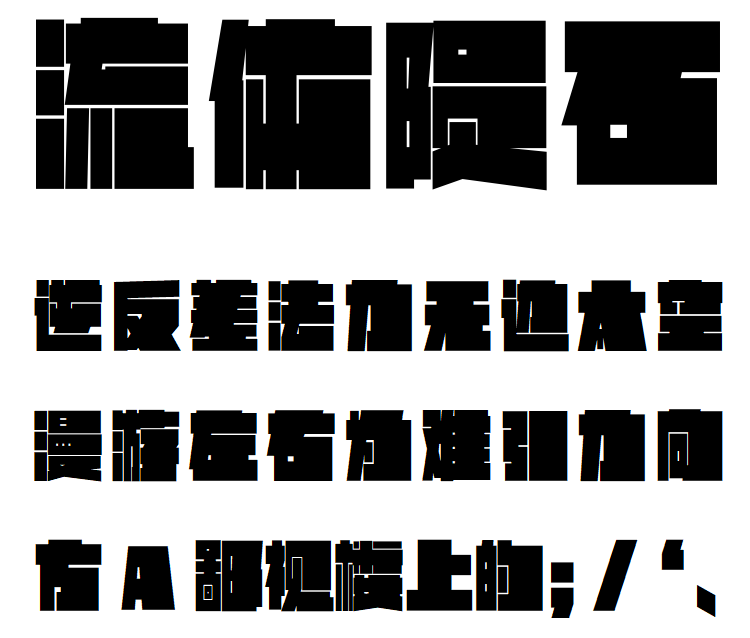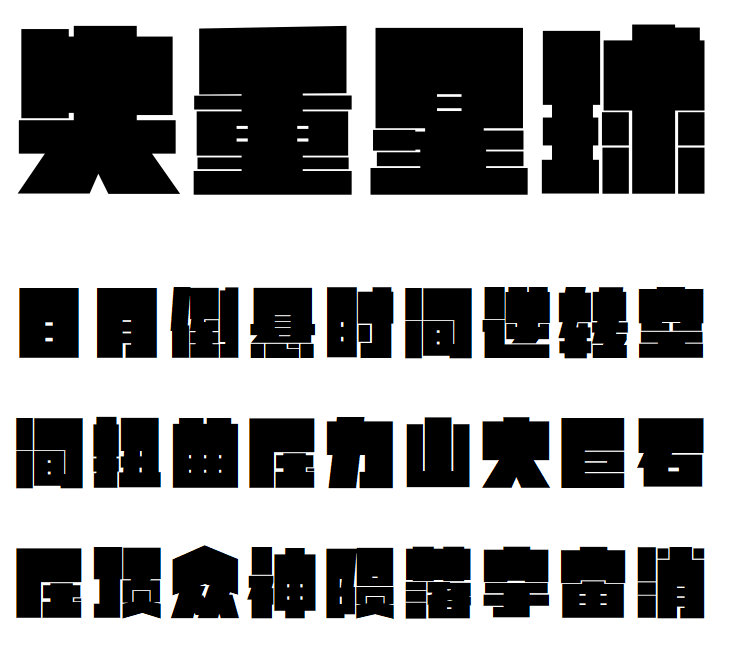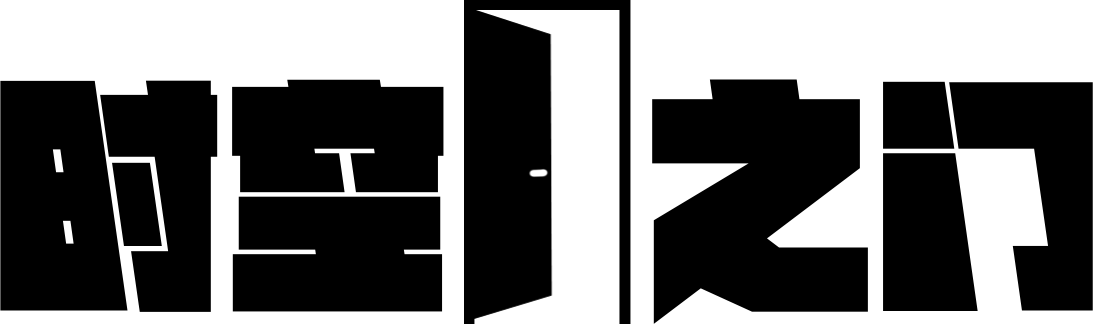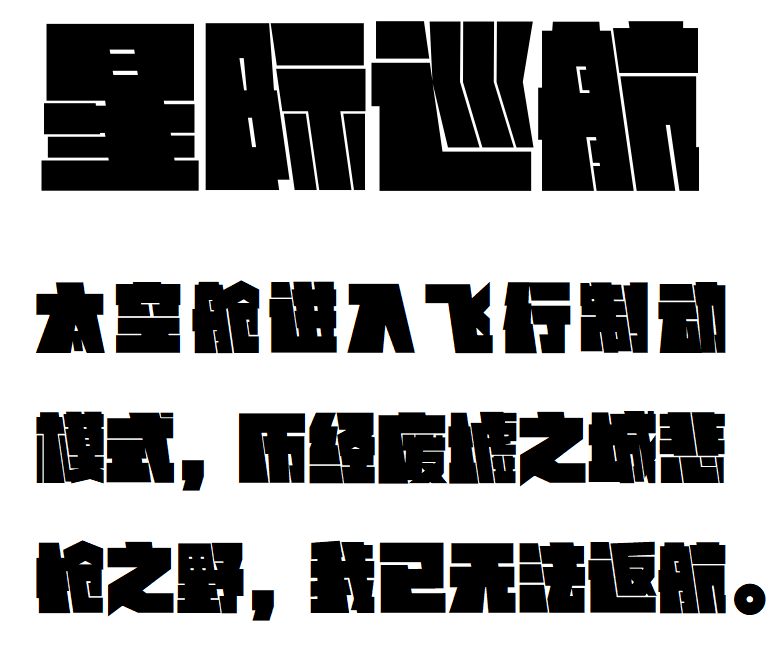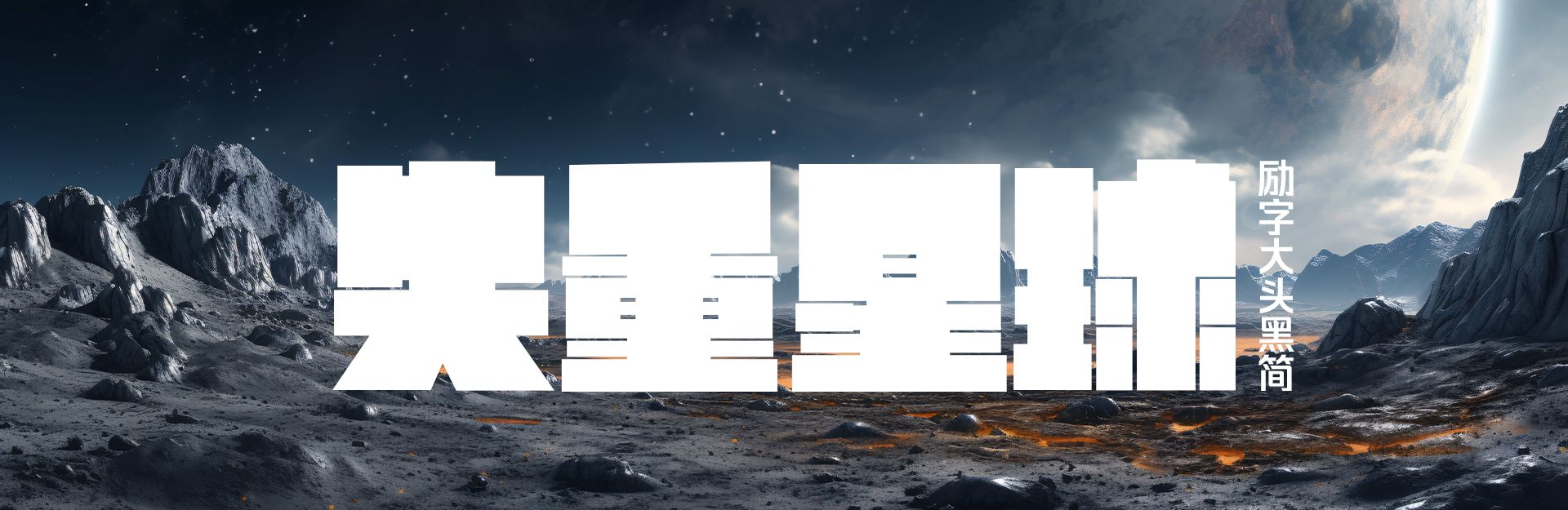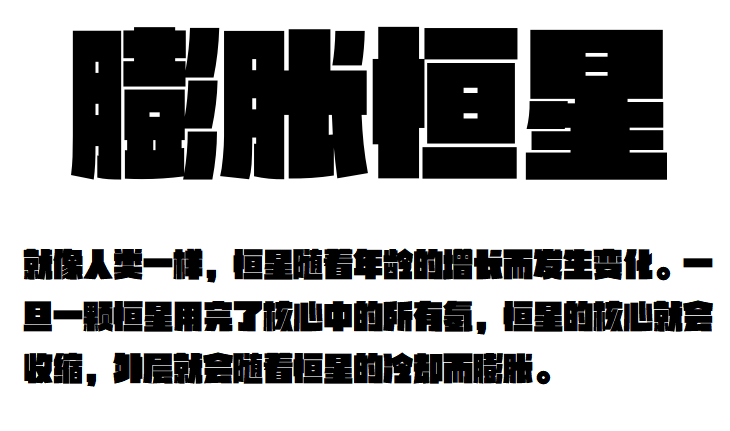
异时空破壁:4款逆反差字体,汉字宇宙的星系巡航之旅
咦
是来自次时空的巡回波段
原来是遗落在遥远外星系的字体探查员
在追寻异星球汉字文明的途中
迷失在汉字宇宙....
励字造梦局紧急启动字有引力模式,
开启时空之门,沿着接收的波段讯号,
巡回迷失的字体探查员,解码次时空的汉字文明。
第一站
星际巡航——励字飞行黑简
漂浮在广阔的宇宙的银河星系,在宇宙的斥力作用下,进行大撕裂演化,形成了一款独特的变形字体——励字飞行黑简。字形方正、中宫宽博、起收笔平直,将左部字体重心向左倾斜,赋予字体独特的视觉张力,整体视觉形象模仿宇宙飞船的飞行状态。
第二站
失重星球——励字大头黑简
在恒星冲撞挤压形成的时空裂缝,励字大头黑简字体内部重心失衡上移,笔画则打破传统规则,粗细组合不均,转折处以直角处理后,形成的一款横平竖直、右侧笔画厚重、左边笔画极细的逆反差直线字体。
第三站
流体陨石——励字宽边黑简
在人类可观测的宇宙边界,流体陨石淹没在宇宙微波辐射中。励字宽边黑简是经受恒星的强力辐射而诞生的一款超认知的极限逆反差字体。左侧字体紧密而右侧字体宽疏,字形方正规整,而重心随字体结构水平移动,以独特的字体组合方式,见证了流体星球的运转规则。
第四站
膨胀恒星——励字跨界黑简